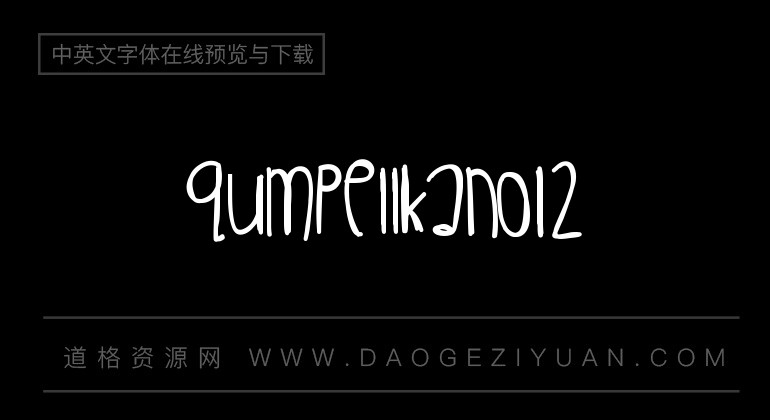
QumpellkaNo12
QumpellkaNo12 是一款非常独特的字体,它的设计灵感来自于德国艺术家和设计师 Julius Klinger 的作品。这款字体具有非常浓重的手写风格,每个字母都有其独特的形式和线条。它也非常适合在大标题和海报等设计中使用,因为它的字母形状非常醒目,容易吸引人们的注意力。 QumpellkaNo12 字体还包含了许多不同的变体,例如斜体和粗体等,因此在设计时可以使用不同的风格来突出文字。这款字体还收到了许多设计师和艺术家的喜爱,被广泛应用于许多印刷品和数字设计中。
QumpellkaNo12是一款非常不错的手写艺术字体,具有很好的视觉感,适合于文化类的宣传设计、商业类品牌的广告和产品包装设计以及个性化文字排版等较多场景。
QumpellkaNo12字符映射图